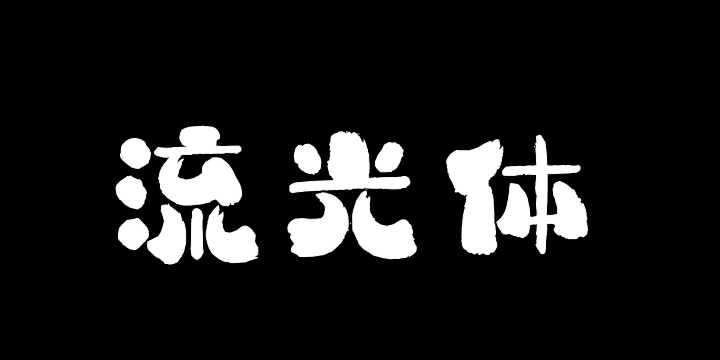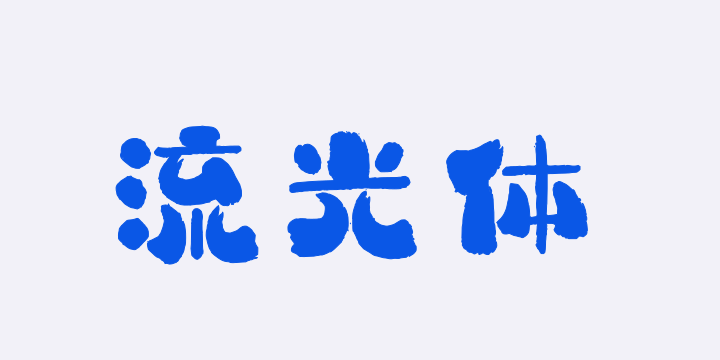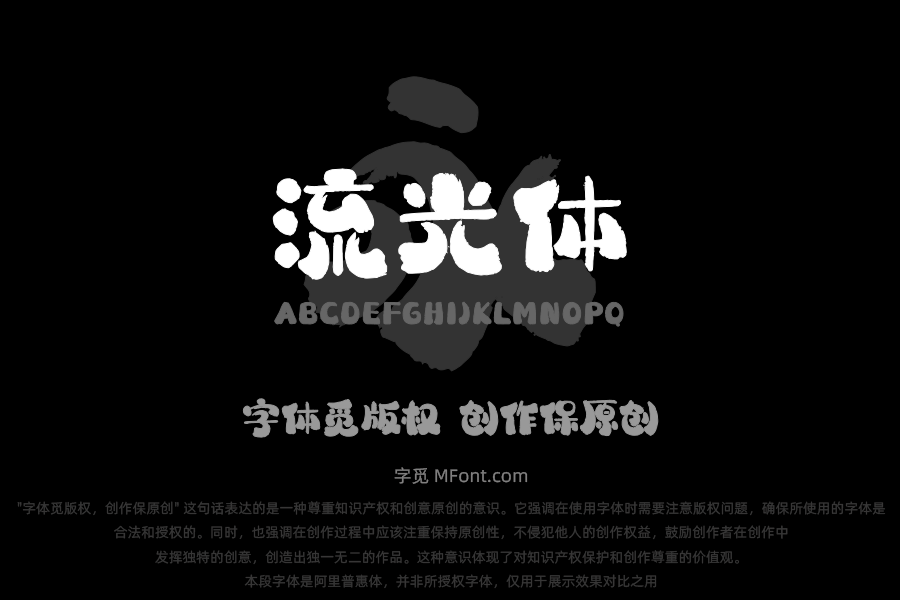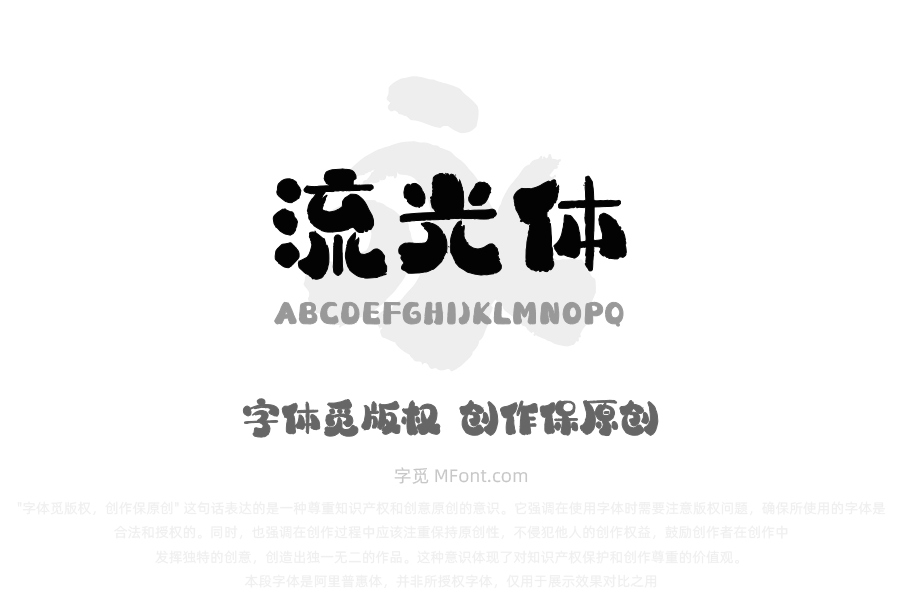
• 上首流光体
字体全名: 上首流光体
字体简介: 上首流光体,简体中文约6763字。这套字体在字形设计上,融合古朴与灵动,笔画如流转光影,既有圆润舒展的形态,又暗含遒劲张力,似时光在笔墨间缓缓淌过。在笔画细节处理上,刻意营造出富有韵律的粗细变化与边缘质感,让每一个字都仿若承载着岁月的流光,于静态中传递出动态的视觉韵律,为文字赋予独特的艺术表现力与视觉吸引力。